С помощью данного генератора заданий можно создать прописи, которые помогут ребенку попрактиковаться в написании букв, слов или словосочетаний. Преимуществом генератора является возможность создания заданий именно с буквами или словами, изучение или закрепление которых необходимо ребенку. Сгенерировать задание можно на украинском, русском или английском языках. В настройках можно выбрать шрифт пунктирными или непрерывными линиями, размер букв и т. д. Задание будет способствовать развитию красивого почерка, мелкой моторики и концентрации внимания.
Для того чтобы сделать буквы прописей черным или серым цветом отметьте текст знаком @ – черный, или # – серый. Пример: @черный@ или #серый#.
Генератор прописей – учим ребенка писать
Научить ребенка писать – непростое дело.
Каждый родитель хочет видеть, как его чадо растет и с радостью изучает что-то новое. Хорошо писать не значит делать это с первого раза, ведь нет таких людей, которые никогда не ошибаются. Именно так же само ребенок не может с первого раза все правильно сделать. В помощь может прийти специально создание прописи, которые сделают процесс обучения намного проще.
Сегодня существуют множество технологий, которые дают человеку буквально все, что ему понадобится в любое время. Не так давно появились специальные программы для обучения одной из таких находок и есть генератор прописей для детей. С помощью такой программы родители могут самостоятельно создать свои прописи. Это даст возможность улучшить грамотность ребенка и тренировать интеллектуальные способности.
Родители теперь могут сгенерировать слова и буквы и таким образом помочь своему ребенку, не спеша освоить азы каллиграфии. Прописи на русском языке – хороший способ з самого детства обучить ребенка языку, даже если он еще не ходит в школу.
Если же нужно изучать иностранные языки, то это также не является проблемой, ведь сейчас есть и прописи на английском языке.
В интернете можно найти много специализированных сайтов. Убедиться в этом можно, набрав в поисковой системе фразу — детские прописи создать самостоятельно программа. Но выбор очень большой и не все они хорошо подойдут каждому ребенку и к тому же не все они бесплатные. Наш сайт Childdevelop предлагает бесплатные прописи на украинском языке и не только. Создать прописи для детей можно на трех языках, а именно украинском, английском и на русском. Главным преимуществом является то, что можно составить прописи самостоятельно с помощью генератора прописей, или другими словами индивидуально для своего ребенка. Кроме этого можно абсолютно бесплатно прописи для детей распечатать и тем самым принести радость себе и неоспоримую пользу своему малышу. Генератор прописей от сайта Childdevelop – это возможность легко, просто и бесплатно обучить своего ребенка письму и подготовить к школе.
Скоро начало учебного года, а значит к вам, коллеги, придут студенты, начинающие изучать русский язык как иностранный с нуля.
Закрепить навык письма, выработать автоматическое правильное и что самое главное понятное написание письменных букв помогают дополнительные занятия с прописями.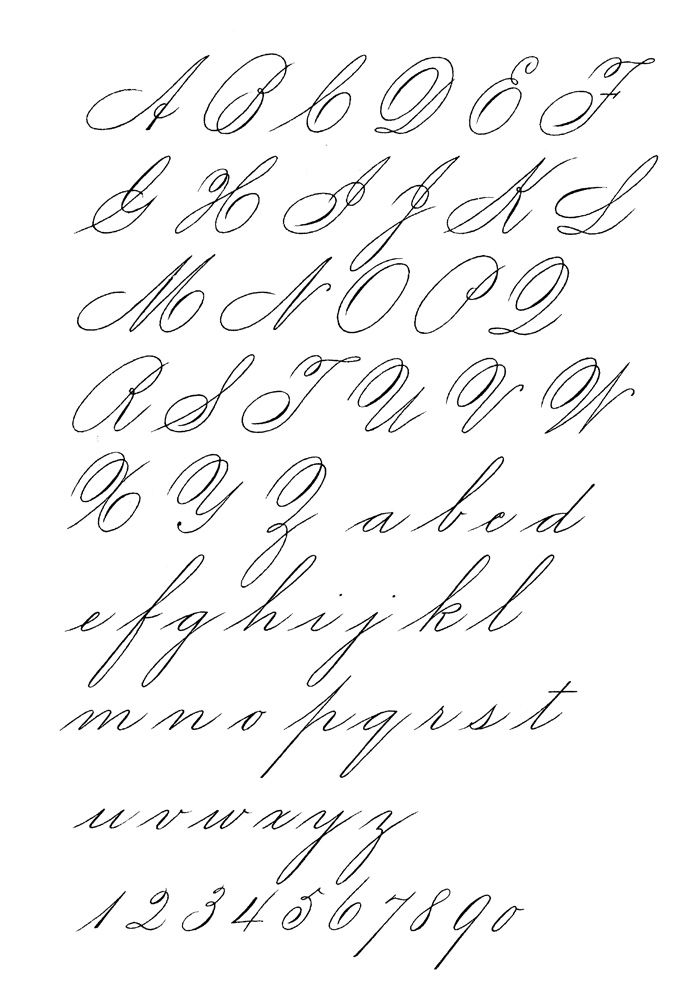
А это значит, что вам понадобятся прописи. Сейчас их легко ( действительно за 5 минут) можно сделать онлайн в интернете.
Нужно только выбрать тот шаблон, который вам нравится, загрузить туда буквы и распечатать. Генератор прописей преобразует введенный вами текст в рукописные прописи, применяя специально созданный каллиграфический шрифт с пунктирной и сплошной линией. И все.
1. Генератор прописей N1 (на русском языке)
Очень простой и понятный сервис. Все на русском языке.
Чтобы составить прописи, выберите на панели нужные вам функции.
Вид страницы: в косую линию, в узкую линию, в широкую линию.
Выбор страницы зависит от степени подготовленности вашего ребенка.
Для написания цифр используйте страницу в клетку.
Вид шрифта: пунктирный, сплошной серый, сплошной черный.
Для обводки букв выберете пунктирный шрифт или сплошной серый.
Для самостоятельного письма по примеру — сплошной черный.
Положение страницы: книжное, альбомное.
В отдельной строке напишите задание.
Например: обведи буквы, пропиши по образцу, пропиши самостоятельно по образцу и т.п.
Далее заполните форму текстом на свое усмотрение.
Это могут быть отдельные буквы, слоги, слова. Пропишите те буквы и слоги, при написании которых у вашего ребенка возникают трудности.